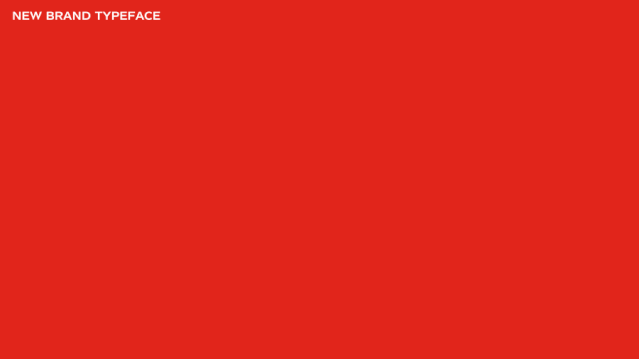
字体名称: 京东朗正体
京东朗正体由方正字库团队主导设计,在定制字体方面经验丰富的汪文、仇寅两位老师担任主创设计师。基于京东品牌的定位,以及一直奉行的客户为先、诚信、协作、感恩、拼搏、担当的价值观,京东朗正体的品牌识别度关键词落脚在了力量感、科技感、直接、简洁、友好五个维度上,并以此为设计理念来发散设计。
京东朗正体字体字库是一款让人赏心悦目、百看不厌的中文字体,适合各类广告和产品包装设计应用,字体大小2.14MB,格式为ttf字体,上传用户是龙猫,作者/版权方为方正/京东